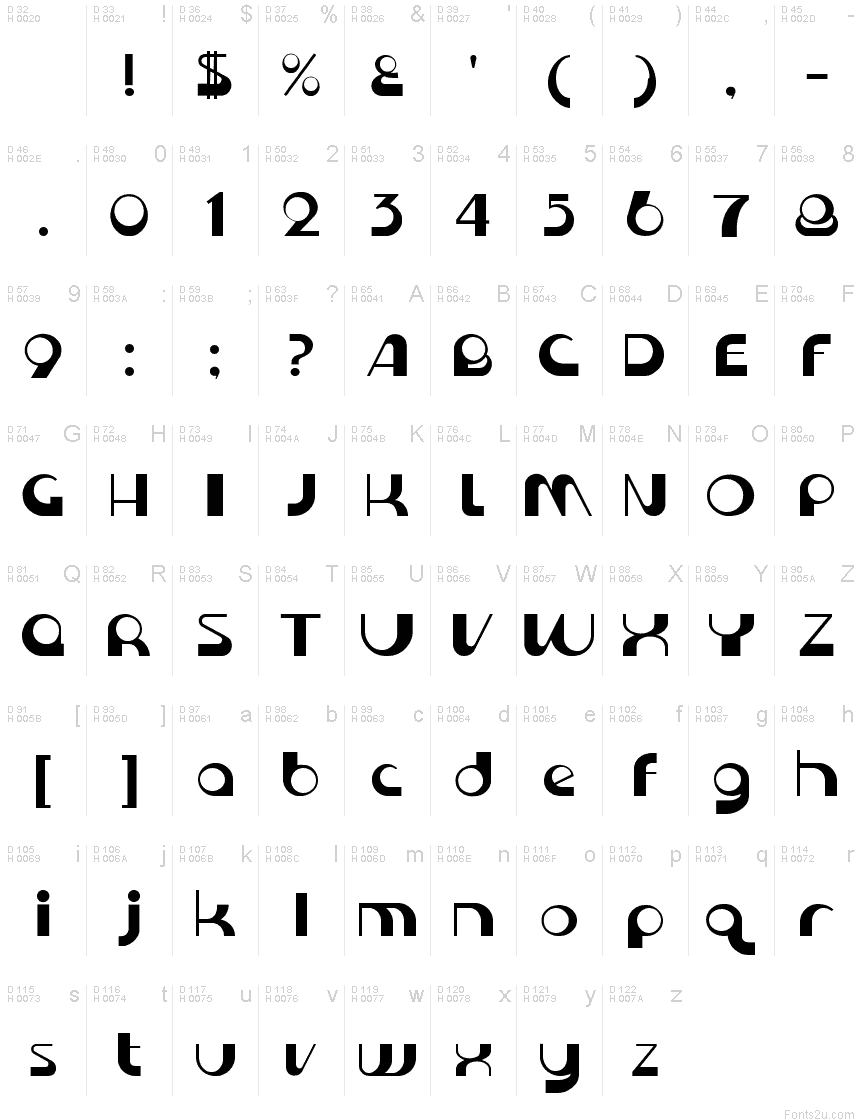
Krome autorstwa Owena Turleya to darmowy, utrzymany w stylu retro font typu display, wyróżniający się zaokrąglonymi, geometrycznymi kształtami i płynnym, spokojnym rytmem. Litery łączą w sobie łagodne krzywizny z prostymi, kanciastymi łączeniami, co nadaje im miękki, a zarazem uporządkowany wygląd, osadzony w estetyce wczesnej ery cyfrowej i automatów arcade.
Krome świetnie sprawdza się w logotypach, nagłówkach plakatów, opakowaniach, okładkach albumów oraz krótkich akcentach redakcyjnych, gdzie zaokrąglona konstrukcja może stanowić fundament projektu. Font jest niezwykle użyteczny: jego znaki są wyraziste, ale nie przytłaczają, co pozwala na tworzenie mocnych nagłówków i elementów brandingu przy zachowaniu przejrzystego, lekkiego układu.